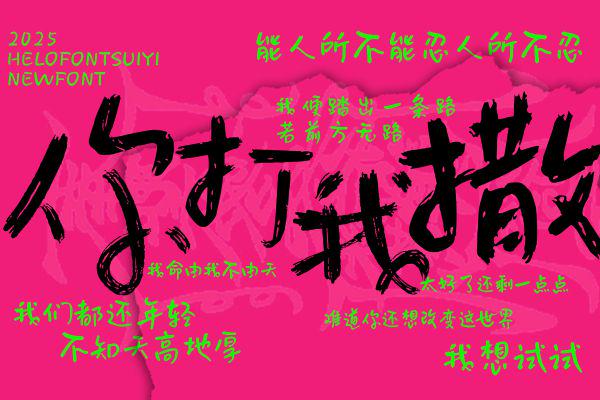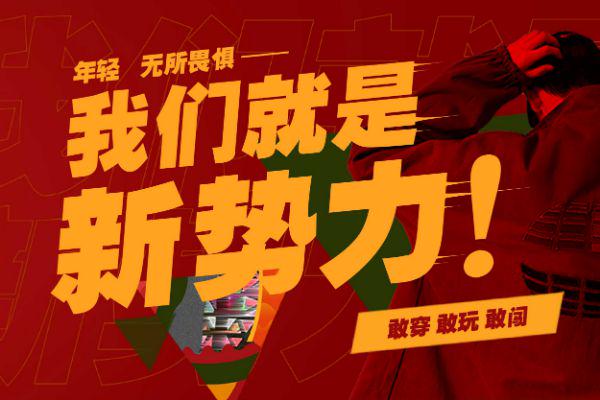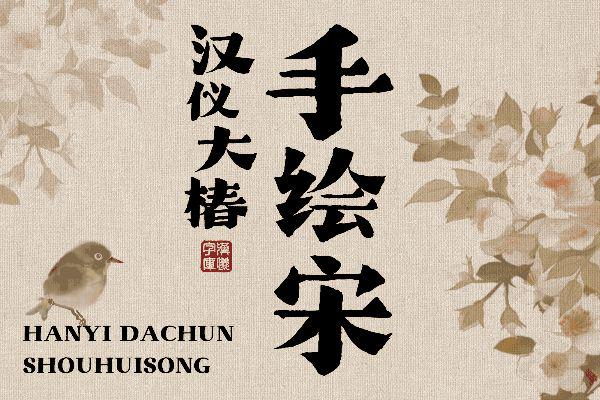
综艺节目字体怎么选?综艺节目常用字体推荐
在当今这个视觉至上的时代,综艺节目早已不再是单纯的内容输出,它们更是一场场精心策划的视觉盛宴。而综艺字体的使用不仅关乎美观,更关乎效率、情感与品牌识别。那么,究竟哪些字体能够在这场视觉角逐中脱颖而出,成为综艺节目制作人的心头好呢?本文整理出 7 款在综艺行业备受好评的字体素材,它们不仅富有表现力,又能兼顾可读性,与节目内容完美融合,为你的综艺节目增光添彩。接下来,一起来看看是哪 7 款字体吧!
1、字由随意体
在综艺节目的视觉设计中,活力与趣味性常常是设计师追求的首要目标,字由随意体正是一款将这两种特质融合得恰到好处的字体。它并非刻板的几何线条,而是带有一种手绘般的自然感,笔画的粗细变化和偶尔出现的不规则处理,都为它增添了几分俏皮与灵动。
在综艺节目的应用场景中,它特别适合那些以轻松搞笑、互动性强为主题的内容。例如,在游戏环节中提示规则,或是展示嘉宾的趣味发言时,它能够瞬间打破屏幕的沉闷,营造出活泼、愉悦的氛围。该款字体是【字由】站内提供的经典字体之一,我们可以访问字由官网来进行使用。
2、逐浪经典粗黑体
当综艺节目需要传达一种力量感、冲击力或是现代时尚感时,逐浪经典粗黑体便是一款值得深入考量的字体。它以其硬朗的笔画、清晰的结构和恰到好处的视觉重量,在综艺设计领域占据了一席之地。这款字体在设计上融合了现代黑体的简洁与综艺所需的表现力,其笔画边缘通常处理得较为锐利,赋予了字体一种干练、果断的视觉感受。
它的字面宽大,重心平稳,保证了在各种屏幕尺寸和播放环境下都能清晰呈现,避免了因字体过于纤细而在动态画面中“消失”的尴尬。在保持专业度和力量感的同时,又不失综艺节目的时尚气息,是追求视觉冲击力与现代感的制作团队的得力助手。该款字体在【字由】中也可以搜索使用,同时字由还提供了多款适合综艺行业的字体素材,欢迎前往访问了解。
3、汉仪大椿手绘体
在众多字体风格中,手绘体以其独特的艺术感和强烈的个性,在综艺节目中拥有不可替代的地位。汉仪大椿手绘体这一类别,顾名思义,它模拟了手写或手绘的笔触,通常带有不规则的粗细变化、自然的起伏和一些“不完美”的细节,正是这些“不完美”赋予了它独特的魅力和人情味。
它非常适合用于那些强调真情实感、生活化场景或需要营造亲切感的综艺节目。比如,在访谈节目中展示嘉宾的内心独白,或是亲子类节目中记录孩子们的童言稚语,活力手绘体能够瞬间拉近观众与节目内容的距离,让文字仿佛拥有了温度和情感。
4、汉仪字研卡通体
汉仪字研卡通体通常拥有夸张的造型和活泼的色彩倾向,能够瞬间抓住观众的眼球,营造出欢乐、轻松的氛围。在儿童类节目、动画短片式综艺环节、或是任何需要注入童趣和幽默感内容的理想选择。例如,在展示有趣的道具名称、游戏积分、或者人物的可爱昵称时,综艺卡通体能够使得文字本身成为视觉焦点,增加画面的趣味性。
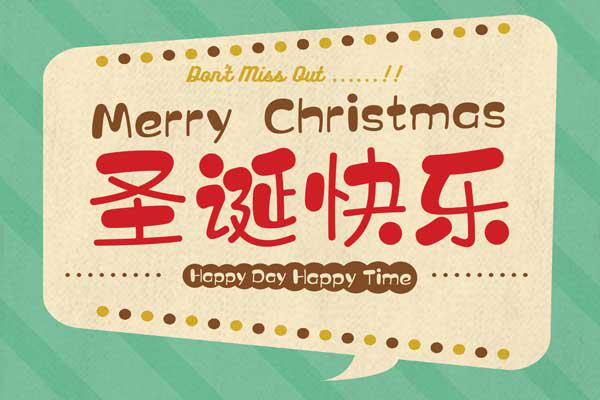
5、那么热爱几何体
随着审美趋势的演变,现代感和设计感成为越来越多综艺节目追求的视觉风格。那么热爱几何体以其简洁、规整的线条和精确的结构,为综艺设计带来了前卫而又不失高级感的选择。这类字体通常以直线、圆弧等几何元素构成,笔画粗细均匀,字形结构严谨,给人一种干净利落、科技感十足的视觉体验。
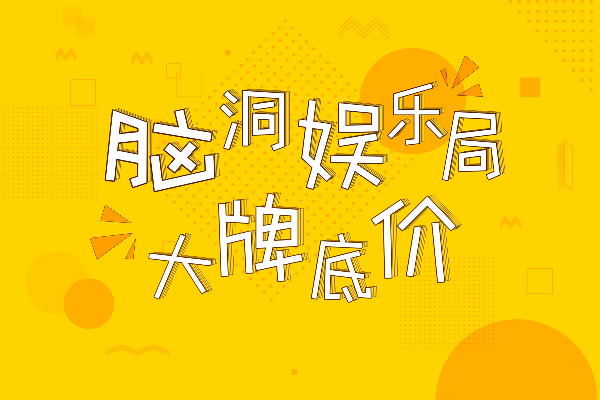
6、点字飒爽手写体
在综艺节目中,有时我们需要表达一种强烈的态度、一种直接的情感,或者一种不羁的个性。点字飒爽手写体正是为此而生。这类字体模仿了大胆、有力度的手写笔迹,笔画通常粗壮、边缘不拘一格,甚至带有一些飞白或墨迹的痕迹,充满了原始的力量感和未经雕琢的真实感。在实际使用体验中,粗犷手写体能够瞬间抓住观众的注意力,非常适合用于强调节目的高潮、转折点、或者人物的激烈情绪表达。
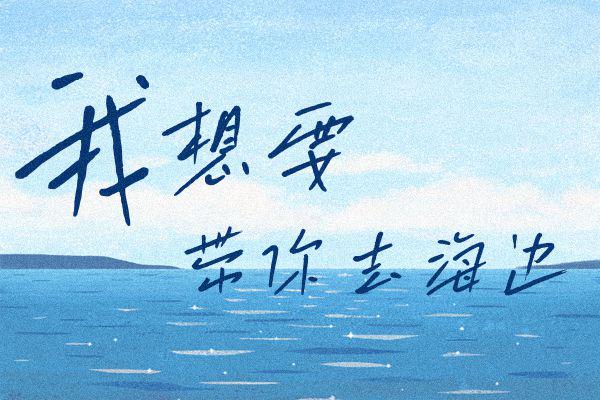
7、字由旷野黑体
尽管综艺节目追求创新和个性,但总有一些经典款字体,凭借其卓越的平衡性、稳定性和广泛的适用性,成为设计师们在各种场景下的 “安全牌” 甚至 “万能牌” 。字由旷野黑体便属于这一范畴。它兼顾了传统黑体的稳重与综艺节目所需活泼度的黑体风格。这类字体通常字面宽大,笔画结构清晰,重心稳定,在保证高可读性的前提下,通过适当的圆角处理或笔画细节变化,使其更具亲和力。
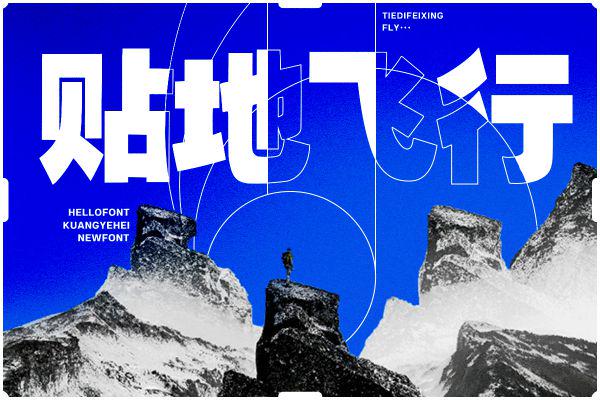
在实际的综艺字体使用场景中,我们不仅要关注字体的单一美感,更要将它们置于节目的整体语境中去考量。思考节目的主题、目标受众、情感基调以及播放平台,选择能够与这些元素完美契合的字体,才能真正发挥字体的最大效用。最好的字体选择并非一成不变,而是根据节目的独特需求量身定制。希望本文推荐的这 7 款能为你带来一些字体使用方面的启发,助您打造出更多引人入胜、深入人心的荧幕作品。